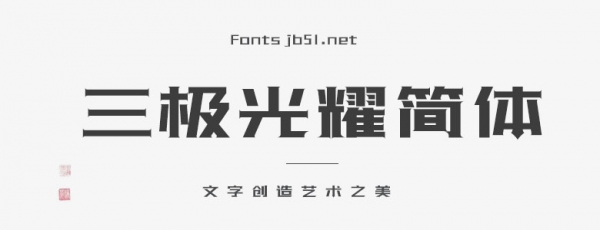
三極光耀簡(jiǎn)體是一款非常有個(gè)性的字體,采用大字面,橫細(xì)豎粗,顯得字形穩(wěn)定扎實(shí)。整個(gè)字體以方形為結(jié)體,彰顯大氣且明快有力。每個(gè)字棱角分明,鋒芒畢露。在字體的結(jié)構(gòu)上采用了一些建筑的元素,具有建筑造型之感,突顯字體的大氣蓬勃之勢(shì),其豐富的藝術(shù)形象,大大的加強(qiáng)了審美效果。適用制作大型廣告、海報(bào),包括報(bào)刊雜志上的標(biāo)題字,文藝類的書刊、品牌廣告和產(chǎn)品包裝設(shè)計(jì),以及社交網(wǎng)絡(luò)的個(gè)性化用字。